Comic Sans、Papyrus 和有史以来最糟糕的字体
已发表: 2022-04-08我在大学期间和一个平面设计专业的学生约会了一段时间。 我知道你在想什么,但我们的程序是利用那段年轻的天真时期进行其他不明智的实验。 反正她不是我喜欢的类型。
撇开双关语不谈,这是一次丰富的经历,如果我不是对她的手艺漠不关心,我认为我们之间的事情可能会解决。 一个特别的错误是我严重滥用——我的意思是使用——排版最可怕的儿子之一:Comic Sans。 在那之后,一些事情变得震耳欲聋:很少有字体像 Comic Sans 那样受到设计师和外行人的普遍憎恶。
互联网并没有太多同意。 见:一切。
因此,当出现如此响亮的共识时,它引出了一些有趣的问题。 字体可以天生就不好吗? 标准是什么? 还有其他类似被鄙视的字体吗? 他们现在和我在房间里吗?!
是什么让这些字体很烂?
无论犯罪是难以辨认、过度使用还是美观,有些字体简直糟透了。 应该避免那些不幸属于这一类的人,以免他们使您的设计无效和不专业。 也许你正在制作一张名片。 或餐厅菜单。 可能是一个标志? 这无关紧要; 所有这些项目都有一个一致的事实:字体选择是观众接收信息的重要因素。
本文将讨论两种肯定会让任何平面设计师不寒而栗的字体。 漫画 Sans 和纸莎草纸。
你们中的一些人可能会想,“贾斯汀,你真的在这里采摘了低垂的果实。” 嗯,这是真的。 近年来,这些字体已被降级为 meme 状态。 并且有充分的理由。 但是,虽然我们将选择这些具体示例,但整篇文章中的要点将在评估任何字体时为您提供帮助。 我们将剖析是什么让这些字体如此令人讨厌,这样我们就可以很容易地发现其他字体的类似缺陷。
事不宜迟,让我们撕开这些印刷暴行。
漫画无
长期以来,这种字体因其孩子气和顽皮的举止而受到嘲笑。 我们嘲笑它笨重、过时的外观,以及它能够立即唤起用户的业余爱好。 当然,它有相当多的道歉者。 (Sus.)但是这种特殊的字体是什么让它如此独特地不讨人喜欢呢?
它管理体重很差。
您可能听说过“很好地承受体重”这句话。 也许是在感恩节晚餐时一位狡猾的阿姨的反手恭维的背景下。 只有我? 嗯,它指的是某人或某物以视觉上不冒犯的方式均匀分布其重量的能力。 Comic Sans 完美地体现了它的含义——无论如何,在印刷方面——不能很好地承载你的体重。
像许多无衬线字体一样,Comic Sans 的笔画相对均匀。 这是因为它具有未调制的字体,这意味着字符的粗细几乎没有对比。 然而,与 Ariel 或 Helvetica 等其他未调制的无衬线字体不同,Comic Sans 没有考虑到茎和肩连接点处的额外厚度。 (那是拱形部分与直线部分连接的地方。)这会导致字符不均匀并导致易读性问题。
为了比较,我们可以看一下 Helvetica 字体。 一种普遍喜爱的字体。 Helvetica 发现肩部与茎部相交处的笔触较细。 Comic Sans 没有进行这种调整,导致了一个不平衡的连接点。
不平衡的外观在正文中被进一步放大,眼睛可以一目了然地扫描整个文本。
它让你看起来像个傻瓜。
Comic Sans 只是有一种令人毛骨悚然的氛围。 这不是一个技术术语——也不是一个词,根据 Grammarly 的裁决——但它肯定是一种感觉。 说到光学,这真的完全是关于感觉的。 绝大多数遇到你的设计的人都没有平面设计学位,他们也不会将技术理论应用到你的工作中。
然而,他们将依靠他们的直接感官告诉他们,让我们面对现实吧:这种字体模仿了孩子的魔法标记涂鸦。 没有魔法。
很少有东西能像使用一种可以被描述为“goobery”的字体那样大胆地否定你的可信度。 说真的,不要强迫我编造文字来正确表达您的品牌身份。 Nix the Comic Sans 用于所有与业务相关的事情,老实说,用于与五岁孩子的生日邀请无关的任何事情。
这是误解的受害者。
Comic Sans 名声不好,但也许应该归咎于设计师。 这是正确的。 说不定还是我的前女友错了。 Comic Sans 虽是卑微的耻辱,但实际上是受害者。 在这里忍受我。
1995 年,就在计算机成为个人家庭必备品的时候,微软试图创建一个程序,让新用户熟悉这个平台,让它接近你的家。 而且,由于某种原因,涉及 Comic Sans 的所有内容都需要完全荒谬,因此他们将其命名为 Microsoft Bob。 如果您从未听说过 Microsoft Bob,那是因为它有点失败。 梅丽娜·盖茨甚至在 2017 年的一次采访中称其为“一次巨大的失败”。 我认为这很有趣。
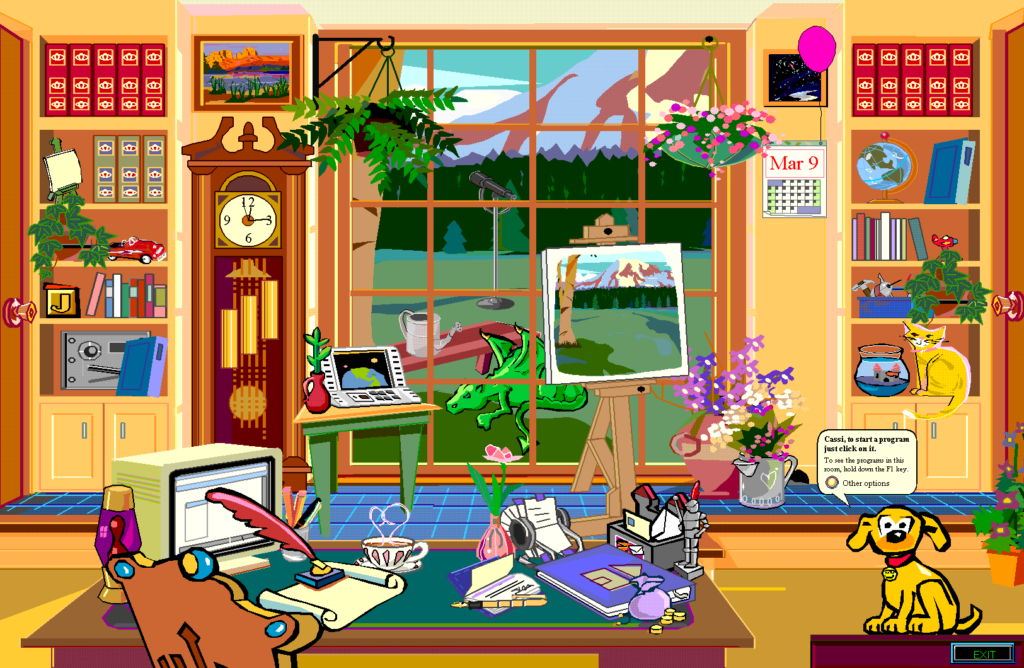
对于那些对 Microsoft Bob 感到好奇的人,去城里看看吧。 但是,这里有一个与 Comic Sans 相关的简洁描述:
微软的礼物
Microsoft Bob 将教新的 PC 用户操作该技术的基础知识。 Comic Sans 由 Vincent Connare 创建,旨在适应该程序。 在那个特定的背景下,正如你从上面的图片中看到的那样,他实际上并没有做得很差。 但是,委托的字体没有及时完成,因此没有在程序中使用。
但命运只是找到了一种方式。 那年晚些时候,当 Windows 95 出货时,Comic Sans 被包括在内。
在某种奇怪的意义上,Comic Sans 被嘲笑是因为它实现了它的目标:为一个愚蠢的程序做一个愚蠢的字体。 试想一下,在与我们平行的宇宙中,我们都学会了如何在 Comic Sans 中使用 Microsoft,最终导致其成为婴儿数字时代遗物的传奇地位。
但这并不意味着它在您的品牌中占有一席之地。 所以,当你的下一个设计任务时,最好避免使用这种字体,以及类似构思错误的字体。
纸莎草纸
也许它最著名(臭名昭著?)的外观是作为詹姆斯卡梅隆 2009 年史诗科幻小说《阿凡达》的字体。 但它的历史更传奇,更悲惨。
纸莎草纸实际上被认为是偶然的起源。 去搞清楚。 它是由 23 岁的 Chris Costello 在广告公司担任入门级插画师期间创作的。 科斯特洛将他的空闲时间投入到制作这种字体中,完全没有意识到它会进入印刷界的耻辱史册。
不出所料,科斯特洛的设计生涯源于书法,他从小就被父亲教过手写字体。 你可以在他的巨著中看到这种影响。 受中东和圣经时代的启发,科斯特洛画了他的涂鸦,最终将他的作品提交给打字公司。 它被所有人拒绝,只有一个:Letraset。
它首先在 Letraset 目录中销售,最终被 Microsoft 授权和收购。
大多数设计师会尽最大努力让你远离某些嘲弄,但让我们试着剖析一下我们最初讨厌这种该死的字体的原因。
太媚俗了。
像大多数手写字体一样,Papyrus 具有一种愚蠢的感觉。 一个古怪的品质,如果你愿意的话。 但肯定不是这些特征的最粗暴的肇事者,对吧? 我的意思是,这不是布拉德利·汉德。
虽然不一定像一些同龄人那样幼稚,但媚俗的价值与其相对过度使用相结合,使 Papyrus 成为一种容易识别的视觉滋扰。 没有人将布拉德利·汉德用作有史以来票房最高的电影之一的片名——上帝保佑我们。
正如我在对 Comic Sans 的抨击中所说,愚蠢的字体会引发对你的设计的愚蠢感觉。 而不是以愉快的方式; 以可怕的、终生的网络欺凌方式受害者。 不建议。
它的形式太大声了。
在选择字体时,这里有一个很好的经验法则:避免使用那些比文本本身更响亮的字体。
使用具有太多字符的字体会在观众的脑海中唤起先前的外观。 想象一下看到星球大战字体用于任何与星球大战无关的东西。 从表面上看,应该不会太冒犯吧? 它本身并没有什么宇宙性,如果有人从洞穴里爬出来,从来没有见证过特许经营的普遍品牌,字体可能不会让人联想到与电影相关的感觉。
但它的个性是巨大的。 如此巨大,以至于如果您看到多个品牌、徽标或带有该字体的图形印刷品,您会注意到它。 你会把它塞进一个关于最糟糕字体的互联网博客。
结论
不幸的事实是,一旦某件事在文化上达成一致,以至于它被授予了模因,就几乎不可能收回它。 所以,如果你执着于使用 Papyrus 作为你的标志、显示文本,或者——最令人震惊的——正文,我只能说:godspeed。